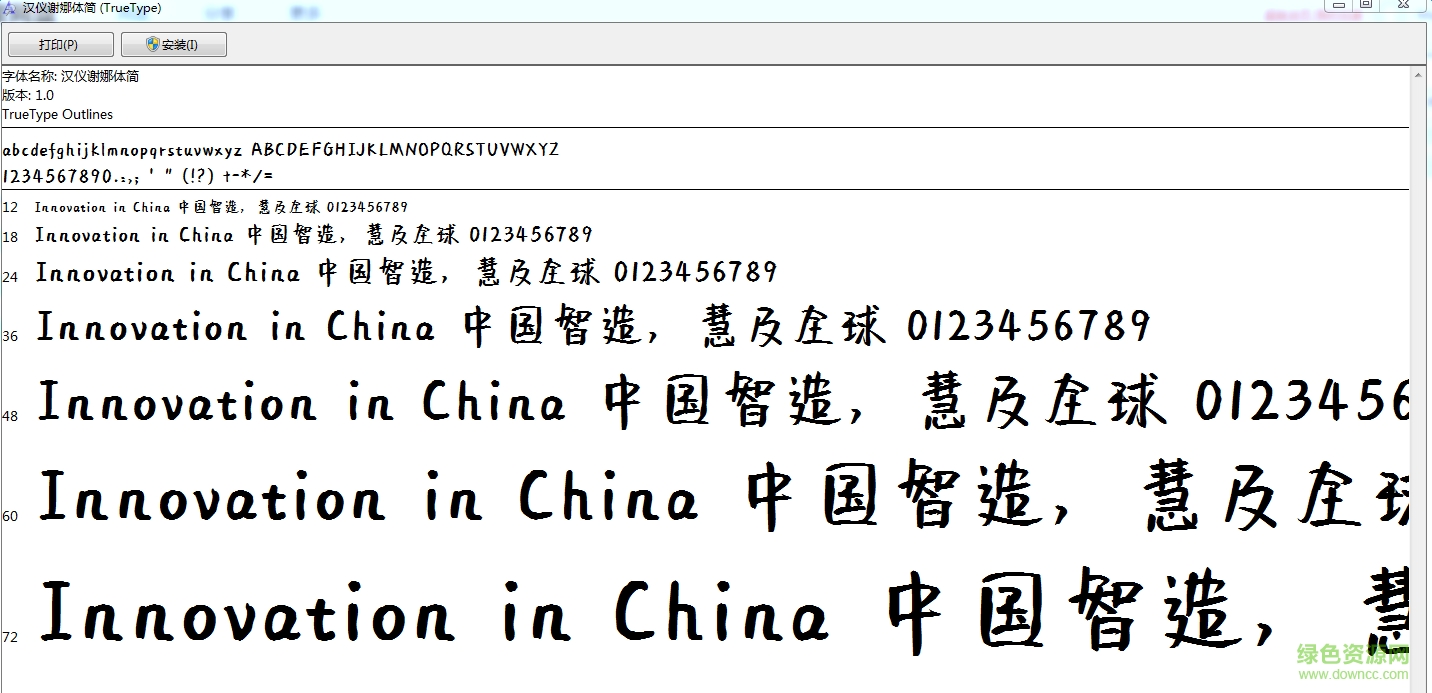
漢儀謝娜字體
漢儀謝娜體ttf是一款漢儀類謝娜字體軟件,謝娜的字體給人非常舒服的感覺(jué),深受廣大年輕人的喜愛(ài),還有更多好看字體盡情期待,歡迎到綠色資源網(wǎng)下載體驗(yàn)!
謝娜的字曝光后,清秀、小巧的字體得到好評(píng)。就在近日,其字體被漢儀字庫(kù)收錄。在謝娜以往詮釋的角色中,少女氣十足,小編此次給大家?guī)?lái)的是漢儀謝娜字體。